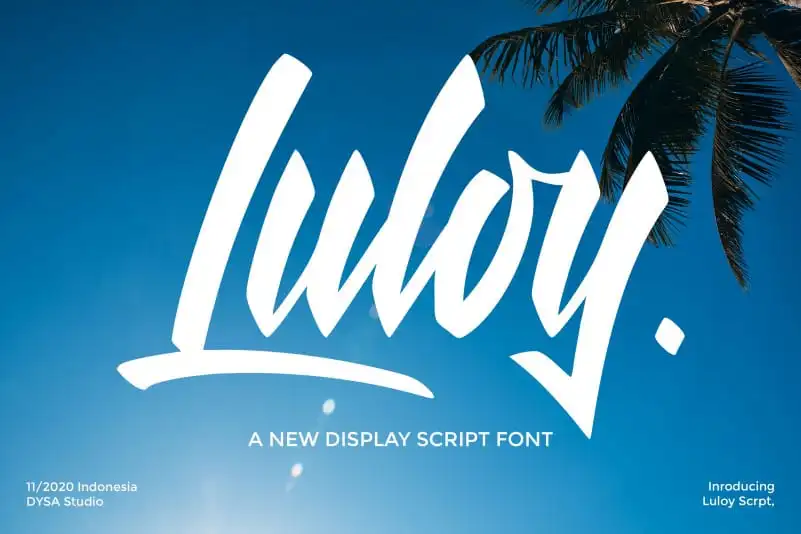
Luloy Script Font – Fonte Grátis
Luloy Script Font
A Luloy Script Font é uma tipografia brush inspirada na escrita a mão clássica. Embora seja uma fórmula casual e descontraída, ela oferece um toque sofisticado que faz dela uma escolha ótima para uma variedade de projetos. Essencialmente criada para branding, logotipos, designs de casamento, postagens nas mídias sociais, anúncios, embalagens e design de produtos, etiquetas, fotografia e até mesmo sobreposições em fotografias, ela complementa perfeitamente qualquer projeto. A fonte é um ativo visual versátil que traz uma dose extra de personalidade para seus materiais digitais ou impressos, tornando-a a escolha ideal tanto para iniciantes quanto para profissionais de design, em todas as categorias de projetos descritas no catálogo.